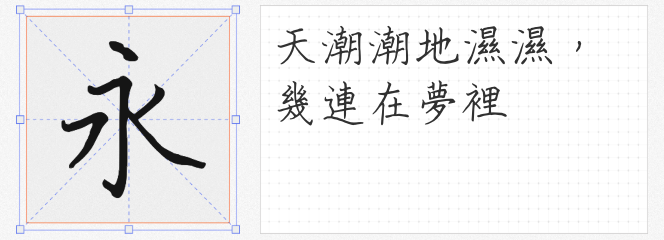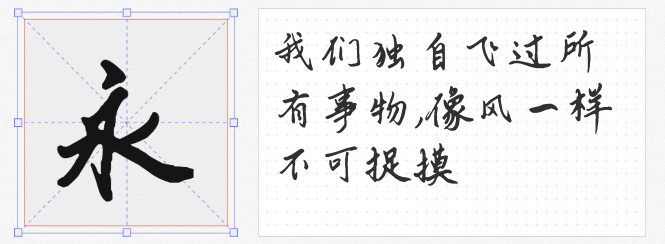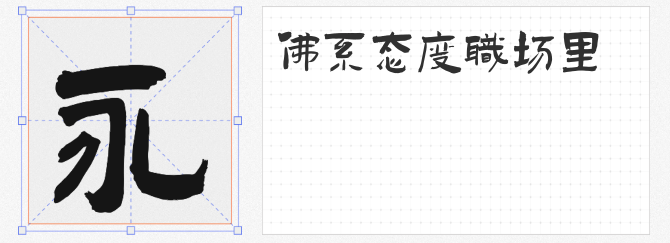
对于设计师而言,字体的选择直接影响作品的视觉调性与专业度。若你正在寻找风格稳重、适用场景广泛的免费商用字体,以下四款精品值得收藏。它们不仅覆盖品牌、海报、书籍等多领域需求,更以独特的设计语言为作品增添文化底蕴与现代美感。
1. 云峰静龙行书
作为云峰字库首款开源字体,云峰静龙行书以行书为基底,将传统书法与现代设计完美融合。其笔画欤侧取代平整,复杂结构被大胆简化,点画间通过勾挑牵丝形成动态呼应,圆转笔触替代方折棱角,整体呈现“端正中见流动”的视觉节奏。这款字体既适合品牌主视觉的典雅表达,也能为文化类海报注入书卷气,堪称传统与现代设计的桥梁。
2. 华光俊秀体
华光俊秀体以高挑字型与刚柔相济的笔触脱颖而出。硬朗的骨架中蕴含柔和的曲线转折,使其既能驾驭科技品牌的理性气质,也能适配时尚领域的优雅诉求。从LOGO设计到电商Banner,从影视字幕到动漫标题,这款字体的广泛适配性堪称“设计万金油”,尤其适合需要平衡专业感与亲和力的商业场景。
3. 随峰体 Beta
由香港设计师阿坤耗时两年手写完成的随峰体,以啫喱笔真实笔触为特色,保留了书写时的顿挫与瑕疵。这种“不完美”反而赋予字体独特的人文气息,适用于需要传递手作温度或个性化表达的设计,如独立品牌包装、文艺活动海报等。开源属性更让这份匠心得以自由传播,为商业项目注入真诚感。
4. 演示佛系体
80岁书法家纪国才创作的佛系体,以繁简交融的笔法构建出超越时代的视觉语言。看似随意的笔触中暗藏结构匠心,非常规偏旁部首组合更带来陌生化美感。这款字体适合文化类、艺术类项目,既能作为书籍封面的点睛之笔,也可为空间设计增添禅意,堪称“阅历可视化”的典范。
这四款字体或承古韵,或显匠心,或展个性,共同以“免费商用”的开放姿态,为设计师提供了零成本的创意素材。无论是追求稳重大气的商业项目,还是渴望突破常规的艺术创作,它们都能成为值得信赖的伙伴。收藏这份字体清单,让设计从此告别“字荒”!